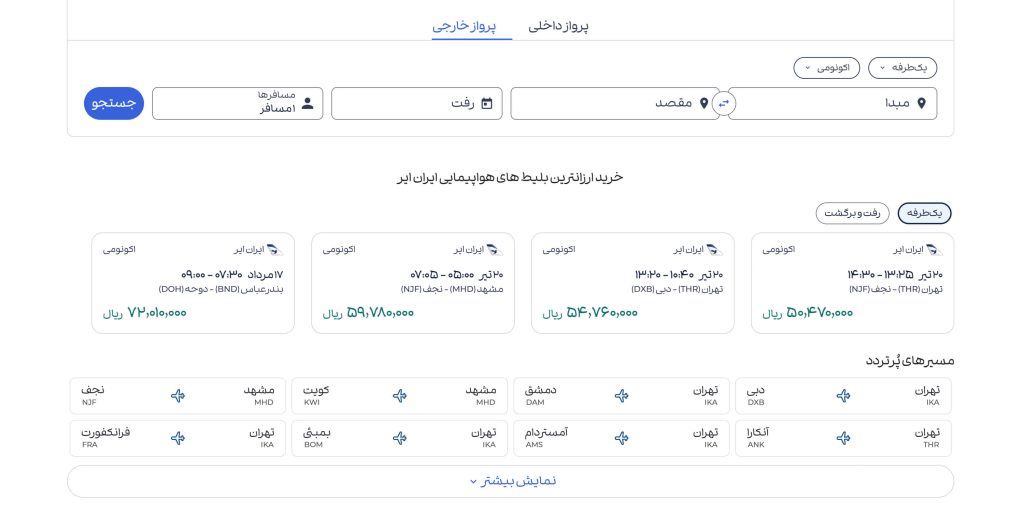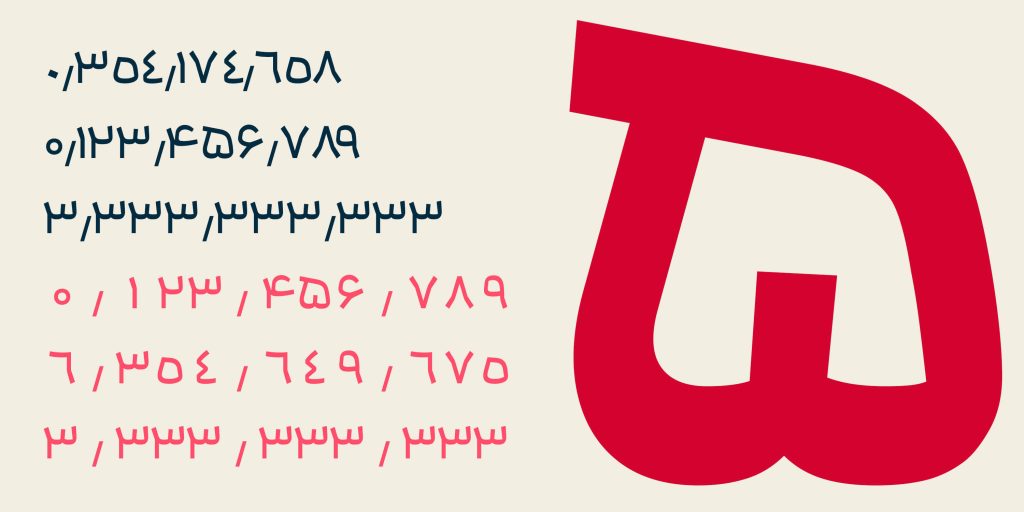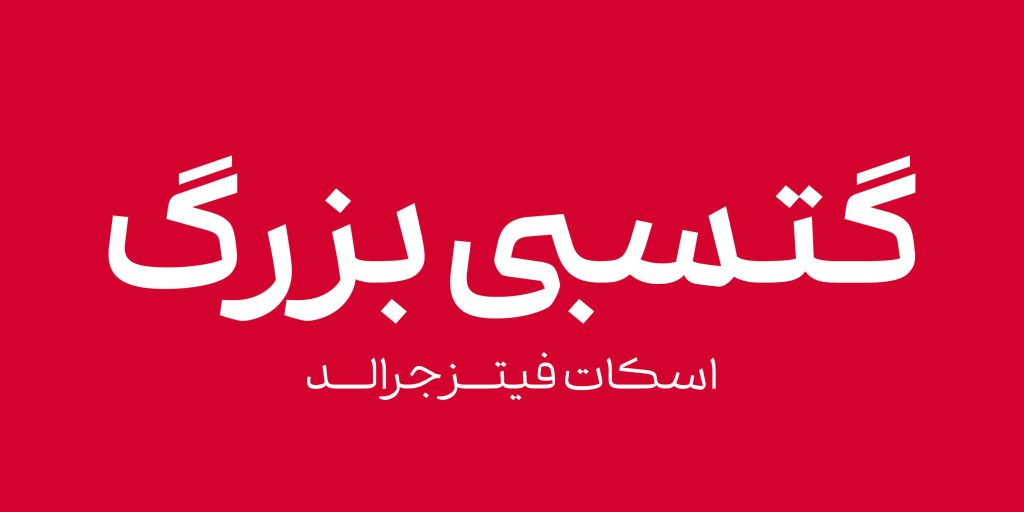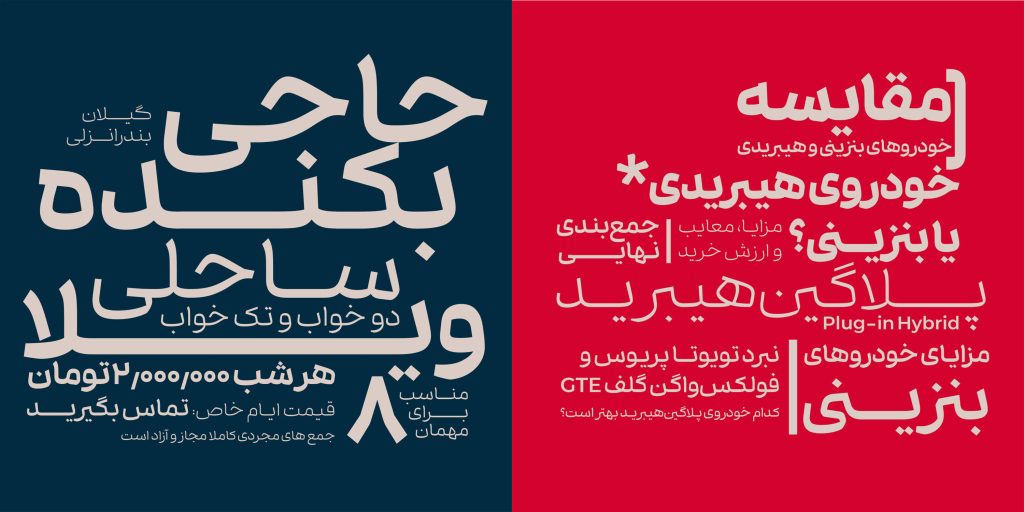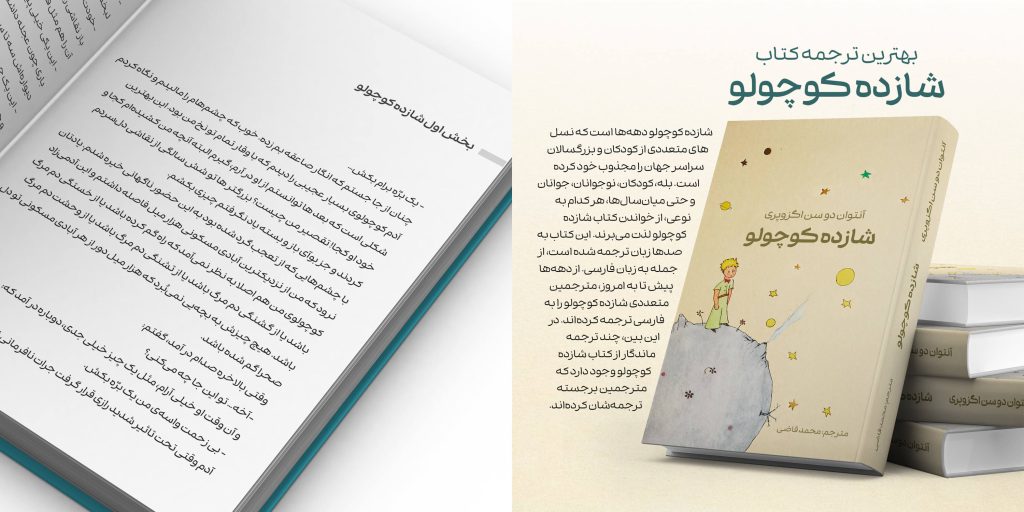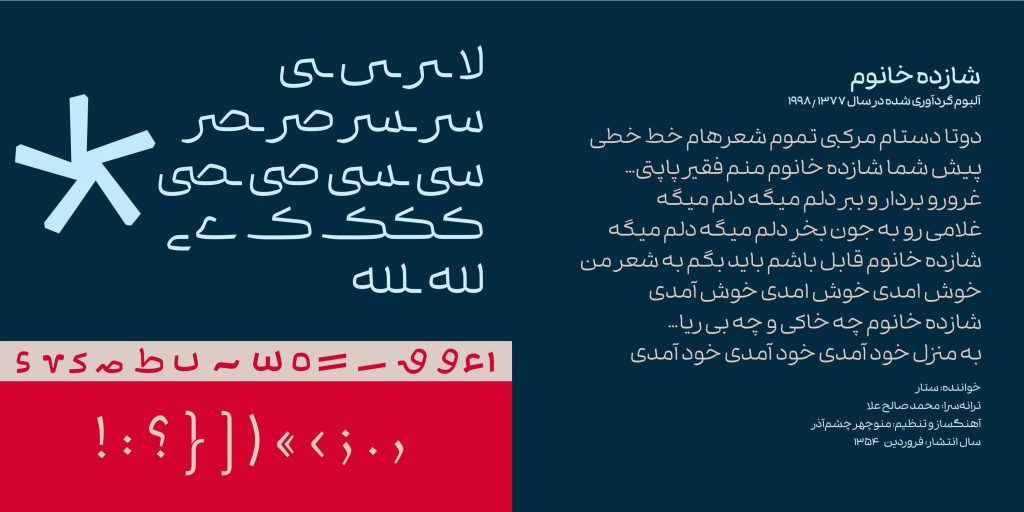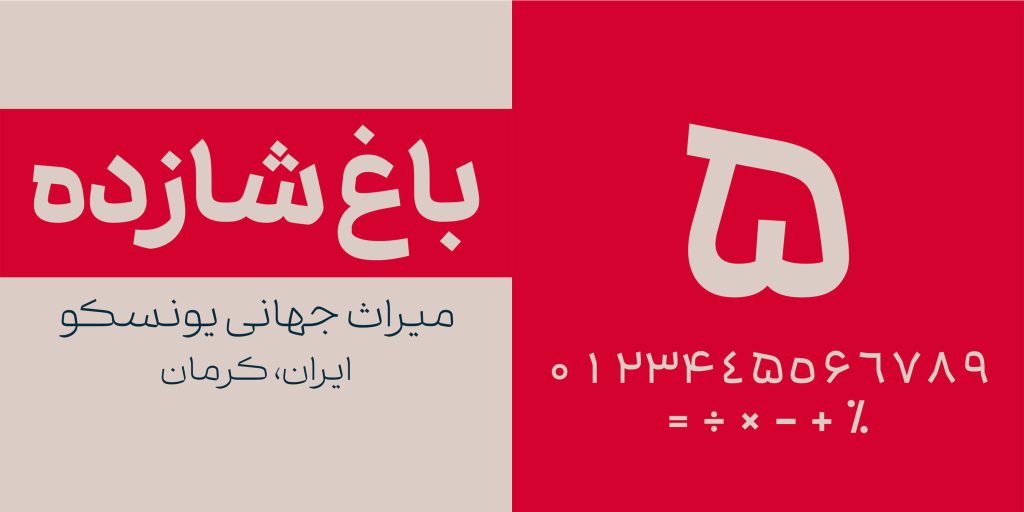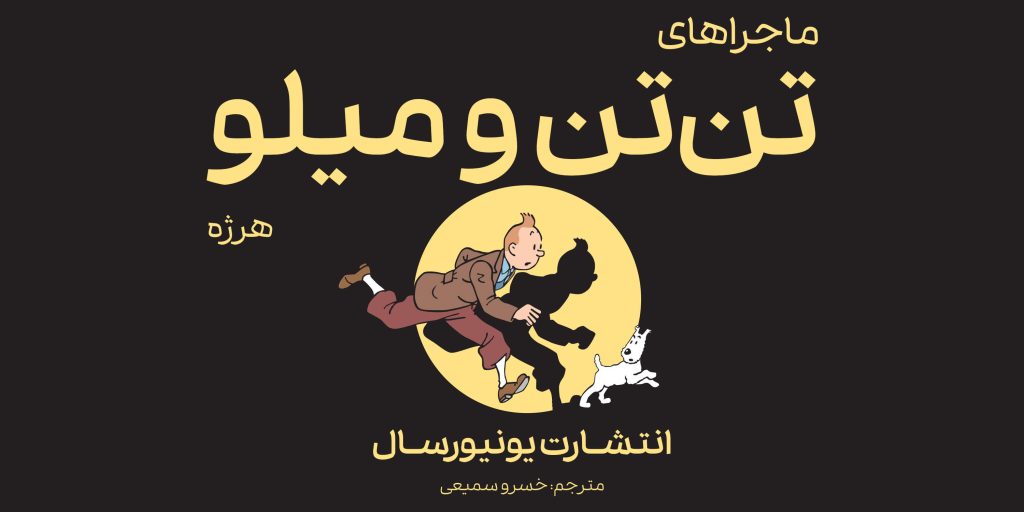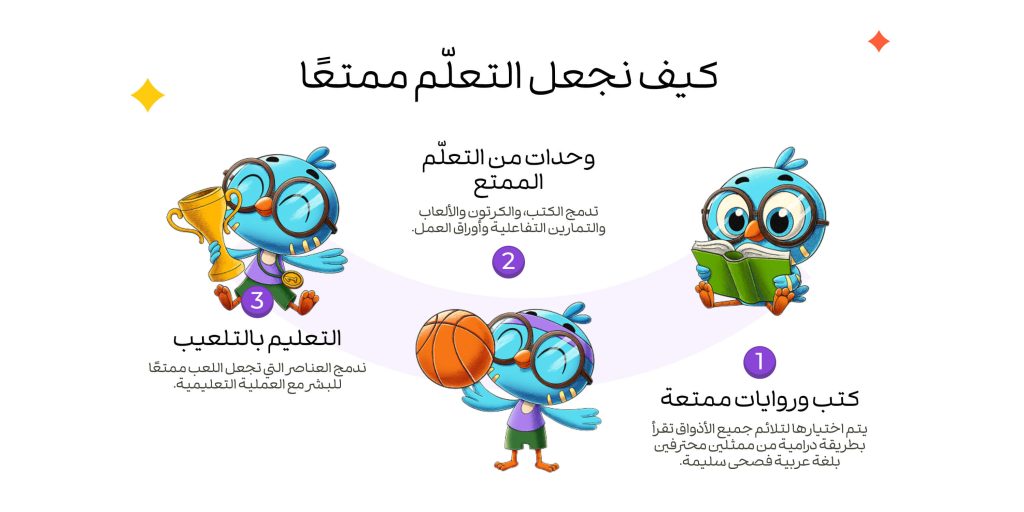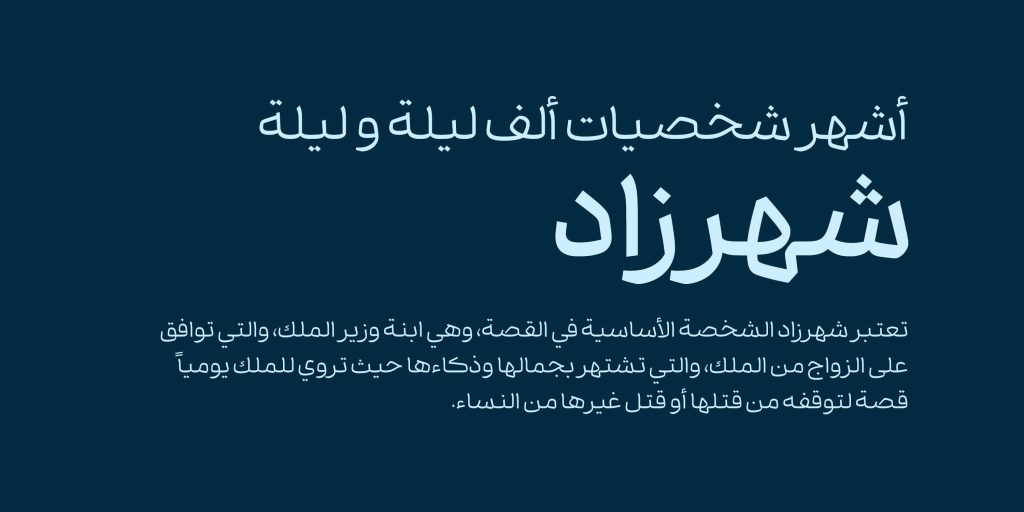
فونت شازده با 8 وزن مختلف و دو سبک نقطه گذاری متفاوت از دسته تایپ فیس های مدرن فارسی عربی است. این قلم از خانواده خط نسخ بوده که تمرکز اصلی خود را بر روی ویژگی خوانایی بالا قرار داده است.
فونت شازده – قلمی با خوانایی بالا
اگر به دنبال تایپ فیسی هستید که دارای خوانایی بالا و همچنین شادابی و عملکردی مطلوب در محیط های گرافیکی و وب باشد بدون شک شازده انتخابی مطمئن است . از شازده می توان در محیط‌هایی مانند وب‌سایت‌ها، رابط‌های کاربری، اپلیکیشن‌ها و متن‌های طولانی بهره مند گردید. این قلم حتی در اندازه‌های بسیار کوچک، کیفیت بصری خود را حفظ می‌کند و بدون افت وضوح، تجربه‌ای روان و خوش‌خوان را به خوانندگان خود ارائه می‌دهد.
شازده را می توان نقطه تلفیق و برآیند زیبایی‌شناسی معاصر با اصول سنتی تایپوگرافی فارسی و عربی برشمرد. این تایپ فیس  نه‌تنها در اندازه‌های ریز عملکردی شگرف دارد، بلکه در متن‌های بلند، مقالات دیجیتال و رابط‌های کاربری پیچیده نیز ظاهر ساختارمند، یکدست و حرفه‌ای خود را همچنان حفظ می‌کند.
داستان شازده
شازده با طراحی آقای رضا بهلول خلق و پیدا گشته است. با دقت در فرم های حروف متوجه نزدیکی این فونت به دسته منولاین می شود که دارای کنتراست خطی بسیار کمی است. رکیبی دقیق از نرمی خط، تعادل هندسی و تأثیرپذیری هوشمندانه از ساختار خط نسخ. هر گلیف به‌گونه‌ای طراحی شده که در محدوده‌ی خود به‌خوبی قرار گیرد، و این دقت، چیدمان متن را در سیستم‌های مبتنی بر گرید منظم و سازگار نگه می‌دارد.
فارسی ،عربی
8 وزن- 2 سبک نقطه گذاری